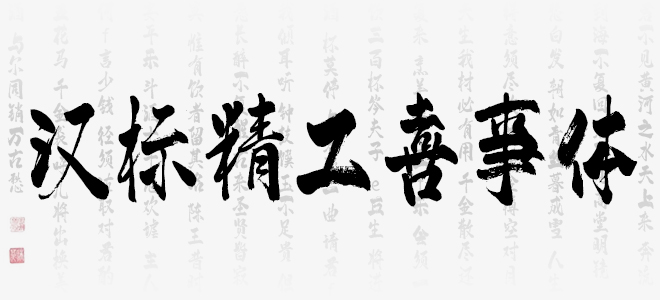
漢標精工喜事體用筆大膽有新意,既有傳統(tǒng)書法筆畫的味道,又加入了作者對當代藝術(shù)的理解。結(jié)體別具一格,充滿詼諧幽默的趣味。適用于文藝類的書刊、品牌廣告和產(chǎn)品包裝設(shè)計,以及社交網(wǎng)絡(luò)的個性化用字。歡迎喜歡漢標精工喜事體的朋友前來下載使用。
漢標精工喜事體